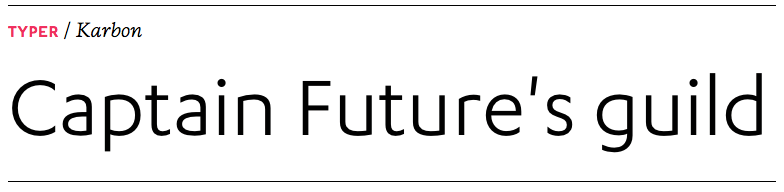
Schrift für Software-Firma
ich stehe gerade vor der Herausforderung für einen Kunden (Software-Programmierungs-Startup) eine Schrift herauszusuchen. Dieser Kunde hat mir zwar deutliche Hinweise gegeben, was ihm nicht gefällt, und dankenswerterweise auch Stichworte wie die Schrift sein sollte, aber ich bin leider mit meinem Latein am Ende.
Was er nicht mochte war die Helvetica. Zu abgenutzt, zu wenig individuell, zu Helvitca. Serifen-Schriften kann er gar nicht leiden, die fallen raus. Er mag die Calibri, weil sie klar und reduziert ist. Gut ausgebaut sollte die Schrift freilich auch sein.  Auf gar keinen Fall darf die Schrift "puschelig" oder kitschig wirken.
Folgende Dinge möchte er durch die Schrift verkörpert sehen:
- freundlich
- kooperativ
- wärme
aber auch
- Science-Fiction (weil Software und Aufbruch und Startup)
- Reduktion
- extreme Klarheit
Für mich hört sich das eigentlich nach einer humanistischen Linear-Antiqua an, aber da haben meine Lieblinge nicht gegriffen. (Vorgeschlagen wurde: Avenir, Realist, Eurostile, alles irgendwie gut aber kein Treffer).
Ich habe ihm mal die Prokyon vorgeschlagen, die er auch gut findet. Leider ist das Minuskel-g ziemlich maniriert. Deswegen kommt die maximal für Überschriften in Frage.
Habt ihr eine Idee? Irgendwelche Vorschläge?
Die Calibri wurde von Luc(as) de Groot entworfen. Jan Fromm, einer von de Groots Schülern, hat eine etwas eckigere Schrift namens Camingo Dos gezeichnet. Diese ist in drei Weiten und als Mono-Familie (Programmierschrift) erhältlich, hat auch ein schickes g wie ich finde und könnte gut zum Thema und Euren Vorstellungen passen.
Hier noch ein paar mehr in dieser Richtung:
• FF Clan
• FS Truman
• Allumi
• Irma Text
• Klavika
• Soho Gothic
• Neo Sans
extreme Klarheit
Schriften, die sich durch ihre Lesbarkeit auszeichnen, sind extrem klar. Alles, was unklar ist, stört den Lesefluss. Wenn aber der Kunde sagt, er könne serifenhaltige Schriften nicht leiden, obwohl Serifen keine Deko sind, sondern der Lesbarkeit dienen oder ihr zumindest nicht im Wege stehen, kann sich die Forderung nach extremer Klarheit nur auf Schaugrößen beziehen. Und damit stellt sich die Frage nach dem Verwendungszweck. Was hat der Kunde also mit der Schrift vor?
Vielleicht ist es sinnvoll, Kunden Schriften, die auch für Texte verwendet werden sollen, die über ein paar Zeilen hinausgehen, gar nicht in Schaugrößen vorzuführen.
Mein Lieblings-Science-Fiction-Roman ist übrigens in der Stempel Garamond gesetzt. Und die klassischen Formen dieser Schrift wirken absolut nicht antiquiert. Ich würde den Roman in keiner Schrift lesen wollen, die nach Science-Fiction aussieht. Vermutlich hat dein Kunde nicht vor, einen Roman zu schreiben, aber ich würde eine Schrift, die nach Science-Fiction aussieht, auch nicht in einem Handbuch lesen wollen.
Nur die FF Cocon wird vermutlich zu flauschig sein für den Kunden. :-D
Lach! Dabei ist die doch so spitz und man muss beim Reinkuscheln aufpassen, dass man sich nicht piekst! :roll:
Gibt es denn schon eine Gestaltung(sidee)?
Schrift darf man sich nicht einfach so angucken, es muss auch immer auf das drumherum geguckt werden. Wenn man sich nur Schriften anguckt, wird man an jeder etwas auszusetzen haben. Vor allem einzelne Buchstabenformen sollten kein Ausschlusskriterium sein, weil man den Buchstaben ja nie einzeln betrachtet und die vermeintlichen Macken verschwinden vielleicht im Text ...
Vor allem einzelne Buchstabenformen sollten kein Ausschlusskriterium sein
Also im Falle der Jenny (FontFarm) ist das q für mich ein Ausschlusskriterium. Gerade bei Text in Lesegraden.